Desde su lanzamiento en 1996, la saga Diablo ha sido un pilar fundamental en el mundo de los videojuegos, definiendo en gran medida el género de los Action RPG (ARPG). Sin embargo, una pregunta ha flotado en el aire durante décadas entre novatos y veteranos por igual: ¿Es Diablo un juego de terror? La respuesta, como el propio lore del juego, es compleja, llena de matices y se encuentra en un oscuro punto intermedio. No es un simple sí o no. Diablo no es un juego de terror en el sentido tradicional, como lo serían 'Resident Evil' o 'Amnesia', pero utiliza los elementos del horror con una maestría inigualable para construir su identidad única, convirtiéndose en el máximo exponente del género de la fantasía oscura.
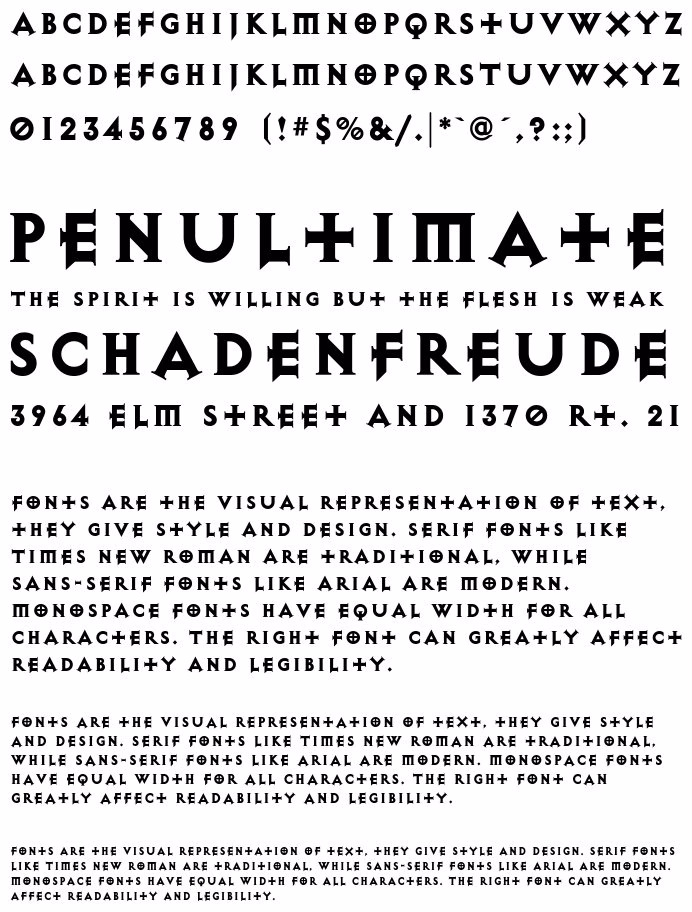
Los Pilares del Terror en Santuario
Para entender el debate, primero debemos analizar los ingredientes que Diablo toma prestados del género de terror. Estos componentes son cruciales para crear la experiencia inmersiva y opresiva que caracteriza al mundo de Santuario. No buscan necesariamente hacerte saltar de la silla, sino generar una sensación constante de desasosiego y peligro.
Una Atmósfera Inolvidable
El primer y más evidente pilar es su atmósfera. Especialmente en el primer juego, la sensación de claustrofobia es palpable. Descender por los niveles de la catedral de Tristram es una clase magistral de diseño ambiental. Los pasillos son angostos, la iluminación es escasa y el sonido es tu peor enemigo. El eco de tus propios pasos, el gruñido lejano de una bestia desconocida, el chirrido de una puerta que se abre en la oscuridad... todo está diseñado para ponerte los pelos de punta. La música, melancólica y ominosa, no ofrece consuelo, sino que acentúa la soledad y la desesperación del héroe. Esta fórmula se ha mantenido y adaptado en toda la saga, con entornos góticos, pantanos pútridos y desiertos desolados que siempre se sienten hostiles y peligrosos.
Diseño de Criaturas y Lore Perturbador
El bestiario de Diablo es una galería de los horrores. No son simples orcos o goblins; son demonios retorcidos, cadáveres reanimados y abominaciones que parecen sacadas de las peores pesadillas. Desde la grotesca apariencia de Andariel, la Doncella de la Angustia, hasta la brutalidad de El Carnicero, cada enemigo está diseñado para inspirar repulsión y temor. El lore del juego profundiza aún más en este horror. Hablamos de un conflicto eterno entre ángeles y demonios donde la humanidad es poco más que un peón. Las historias de posesiones demoníacas, sacrificios humanos, tortura y la corrupción del alma son el pan de cada día en Santuario. Este trasfondo narrativo es profundamente oscuro y pesimista, un elemento clave del horror cósmico y gótico.
Más Allá del Miedo: El Corazón de un ARPG
A pesar de todos estos elementos de terror, la experiencia central de Diablo se aleja del género. La razón principal es que el juego no busca hacerte sentir indefenso; busca todo lo contrario.
La Fantasía de Poder
A diferencia de un juego de survival horror donde el protagonista es vulnerable y el combate es un último recurso, en Diablo eres un héroe de poder creciente. Ya sea como un Bárbaro, una Hechicera o un Nigromante, tu objetivo es convertirte en una máquina de matar demonios. La sensación dominante no es el miedo, sino el poder. Ver a hordas de enemigos explotar en pedazos por tus habilidades es una experiencia catártica y empoderadora que contrarresta directamente la sensación de pavor. El terror existe en el mundo, pero tú eres la respuesta a ese terror.
El Ciclo Adictivo: Botín y Progreso
El núcleo jugable de Diablo es su famoso ciclo de matar monstruos, conseguir botín (loot), mejorar a tu personaje y repetir. La motivación principal del jugador no es sobrevivir a la siguiente esquina, sino encontrar esa espada legendaria o esa pieza de armadura que complete su set. La mente del jugador está ocupada calculando estadísticas, optimizando habilidades y gestionando el inventario. Este enfoque en la progresión y la recompensa es la seña de identidad de los ARPG y desvía la atención de los elementos puramente terroríficos hacia una experiencia de acción y estrategia.
Fantasía Oscura: El Género que lo Define Todo
Entonces, si no es terror puro pero bebe de él, y es un ARPG pero con un tono mucho más sombrío, ¿dónde encaja Diablo? La respuesta es la fantasía oscura. Este subgénero es el hogar perfecto para la saga. La fantasía oscura combina la épica y la magia de la fantasía tradicional con los temas pesimistas, la violencia gráfica y la atmósfera opresiva del horror. El mundo no es blanco y negro, sino una escala de grises manchada de sangre. La esperanza es un bien escaso y las victorias a menudo tienen un coste terrible. Diablo es el ejemplo perfecto de este género, creando un universo donde la heroicidad existe, pero está constantemente amenazada por un mal abrumador y corruptor.
Tabla Comparativa de Géneros
| Característica | Juego de Terror Puro | Diablo (Fantasía Oscura) | ARPG de Alta Fantasía |
|---|---|---|---|
| Objetivo Principal | Sobrevivir, escapar, resolver un misterio. | Derrotar al mal, volverse más fuerte, obtener botín. | Salvar el mundo, completar misiones, mejorar el equipo. |
| Protagonista | Vulnerable, a menudo indefenso. | Un héroe poderoso (Nephalem) que masacra hordas. | Un héroe elegido, a menudo con un destino glorioso. |
| Sensación Dominante | Miedo, ansiedad, tensión. | Poder, adrenalina, desasosiego. | Aventura, poder, heroísmo. |
| Combate | Escaso, torpe, un último recurso. | Constante, rápido, espectacular y central en la jugabilidad. | Frecuente, estratégico y central en la jugabilidad. |
La Tipografía del Infierno: Un Detalle que Construye Atmósfera
La maestría de Blizzard para construir este mundo de fantasía oscura llega hasta los detalles más pequeños, como la tipografía. La fuente utilizada en gran parte de la franquicia es la comercial 'Exocet', aunque existe una réplica gratuita muy popular llamada 'Diablo Heavy'. Esta fuente, con su estilo gótico y casi rúnico, impregna cada texto del juego de una sensación de antigüedad, misterio y peligro. No estás leyendo un simple menú; estás descifrando un texto arcano. Incluso el logo de Diablo 4, aunque fue creado a medida, guarda similitudes con fuentes como 'Bildad', con sus trazos afilados y agresivos que evocan garras o fragmentos de hueso. Es una prueba de que cada decisión de diseño, por sutil que parezca, está orientada a reforzar la identidad oscura y terrorífica de la saga.